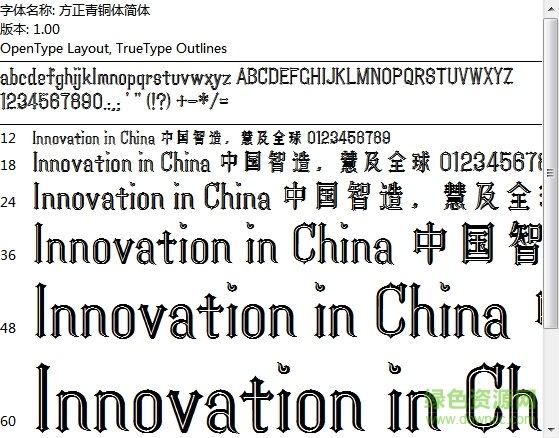
青銅器銘文字體
銘文字體是一款類似于青銅器上的銘文所使用的藝術(shù)字體,有著鏤空的造型而彎曲的結(jié)構(gòu),深度還原了歷史的古典氣質(zhì),喜歡的朋友就來(lái)綠色資源網(wǎng)收藏吧!
銘文字體總稱
銘文,本指古人在青銅禮器上加鑄銘文以記鑄造該器的原由、所紀(jì)念或祭祀的人物等,后來(lái)就泛指在各類器物上特意留下的記錄該器物制作的時(shí)間、地點(diǎn)、工匠姓名、作坊名稱等的文字。在網(wǎng)絡(luò)游戲《魔獸世界》中銘文作為一種商業(yè)技能出現(xiàn)。
銘文字體應(yīng)用
字體特色
銘文又稱金文、鐘鼎文,指鑄刻在青銅器物上的文字。與甲骨文同樣為中國(guó)的一種古老文字,是華夏文明的瑰寶。它不單單是判斷青銅器年代的最重要標(biāo)準(zhǔn),更是器物形制及紋飾方面的標(biāo)準(zhǔn)。青銅器銘文在商周時(shí)期已經(jīng)是一種很成熟的書法藝術(shù),為歷代研究書法的人們所重視。從史料學(xué)的角度來(lái)看,青銅器的銘文因?yàn)榫哂袠O其豐富而確鑿可信的史料價(jià)值,而顯得十分珍貴。古人往往將國(guó)家或宗族的大事銘刻其上,并且表現(xiàn)形式多樣化!